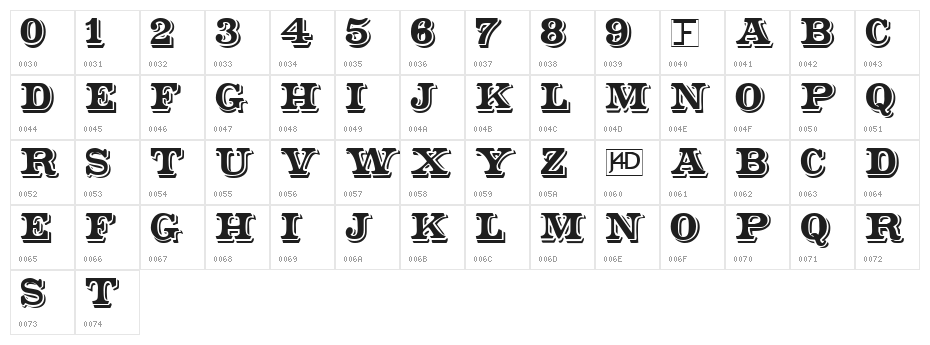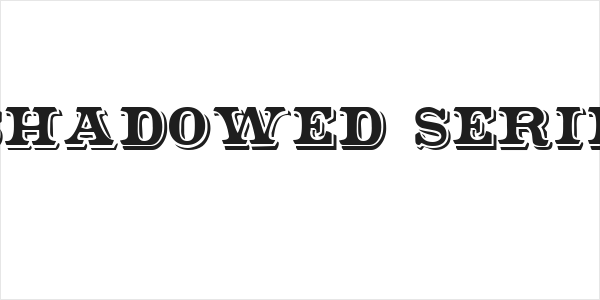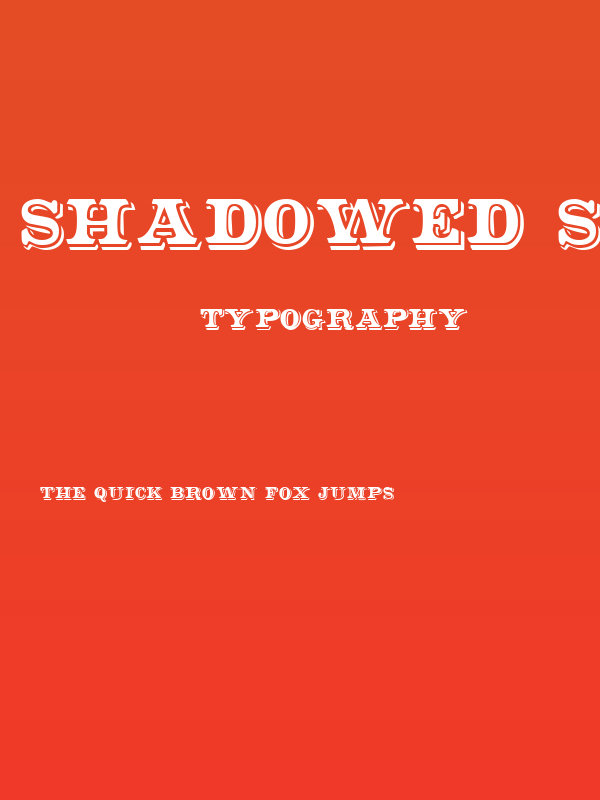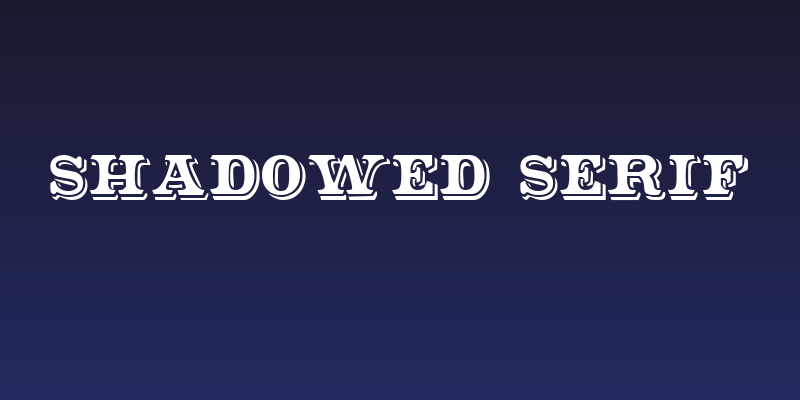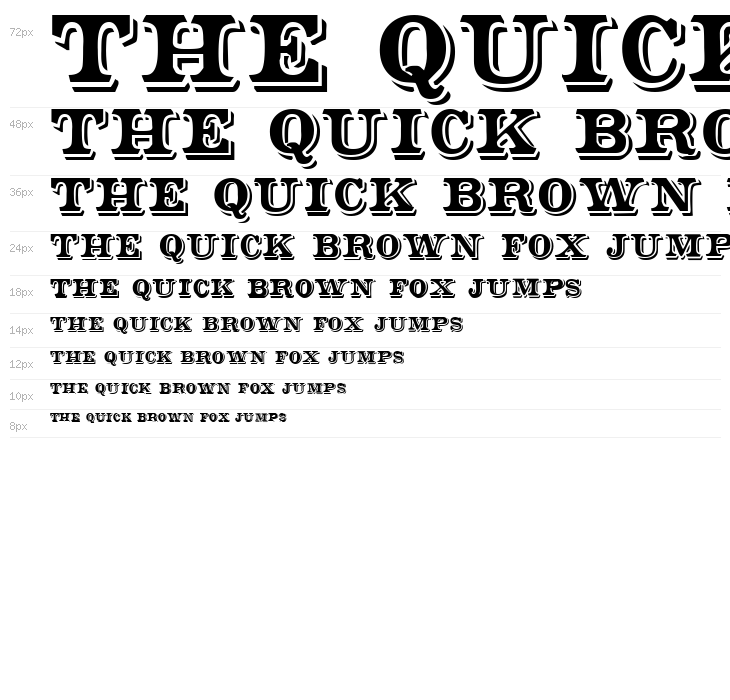
Shadowed Serif Font
| مشاريع مقترحة | Perfect for posters, logos, branding materials, and any design project that requires a bold and impactful typeface. |